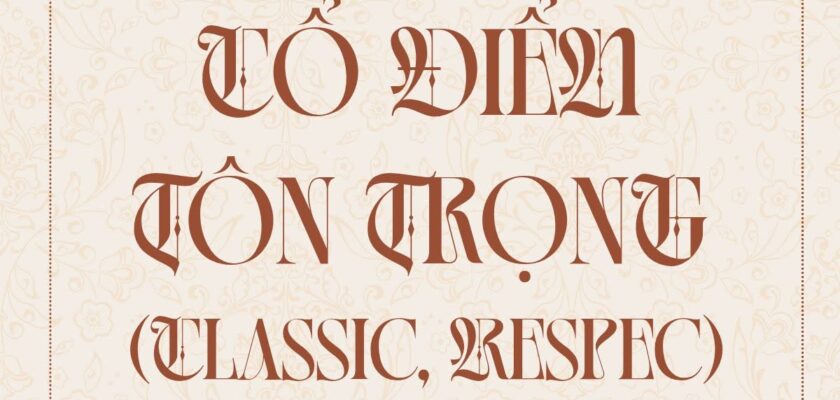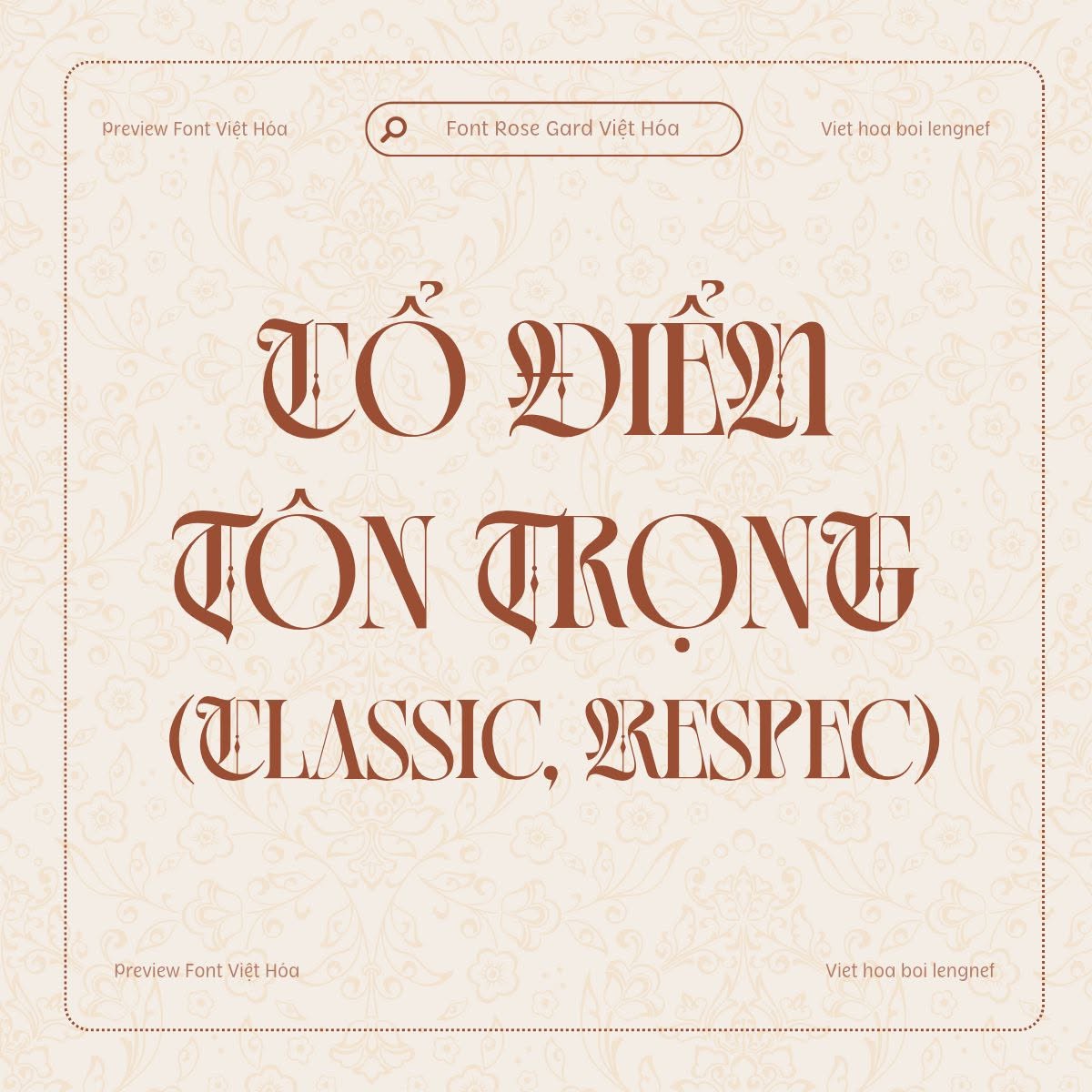
• Tác giả: Handpik Type
• Việt hóa: lengnef
Font LF Rose Gard Việt hóa
Rose Gard là một phông chữ Blackletter hiện đại, mang đến vẻ thanh lịch nhưng mạnh mẽ. Phù hợp cho nhiều dự án: sách, tạp chí, logo, thương hiệu, nhiếp ảnh, trích dẫn, tiêu đề blog, áp phích, quảng cáo, v.v…